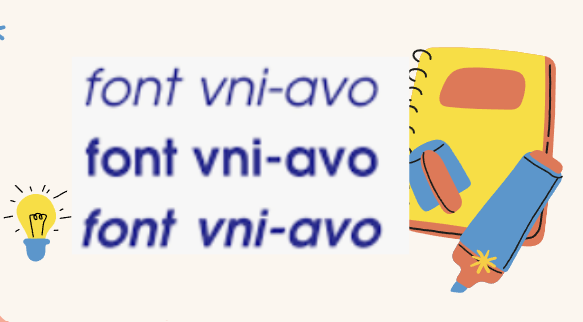
Font Vni Avo Free
Phân loại: Cá tính
Nếu bạn đang tìm kiếm một loại font chữ đẹp và phong cách để sử dụng trong thiết kế hoặc văn bản của mình, thì font VNI Avo chắc chắn sẽ là một lựa chọn tuyệt vời. Font VNI Avo là một font chữ thuộc bộ font chữ không chân. Với các đặc điểm nổi bật như dễ đọc, phong cách hiện đại và sự đa dạng trong kiểu chữ, VNI Avo không chỉ giúp tăng cường tính thẩm mỹ cho tài liệu mà còn phù hợp với nhiều mục đích sử dụng khác nhau. Bên cạnh đó, VNI Avo còn tương thích tốt với nhiều phần mềm thiết kế đồ họa và xử lý văn bản, giúp bạn dễ dàng sáng tạo và tạo dấu ấn riêng. Hãy khám phá ngay font VNI Avo để trải nghiệm sự khác biệt và đẳng cấp mà nó mang lại.